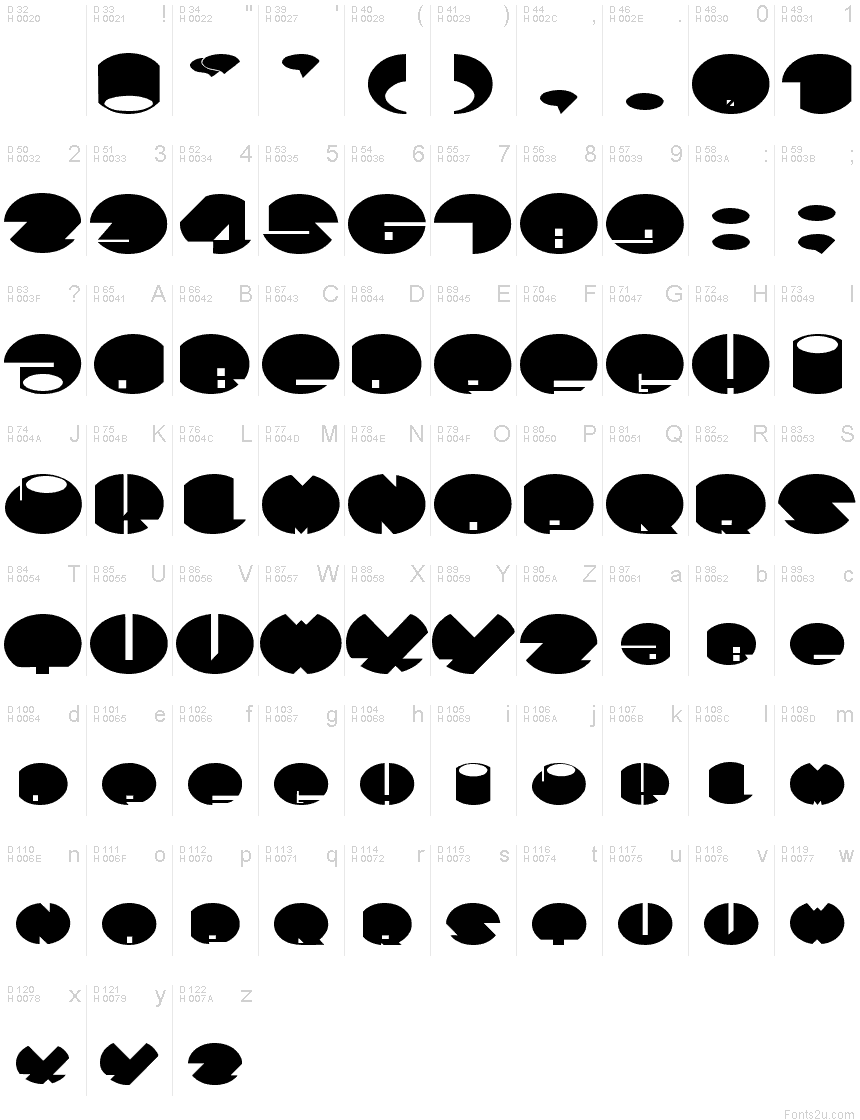
SpaceAce od Font"a"licious Fonts je bezplatné, výrazné písmo v retro-vesmírném duchu. Písmena jsou tvořena těžkými zaoblenými hmotami, které přerušují ostré horizontální řezy a klínovité zářezy. Celému písmu to dodává futuristický nádech „nízké oběžné dráhy“ 60. let, namísto jemného hippie stylu.
Hodí se na plakáty, obaly desek, arkádové letáky, titulky a výrazné obaly, kde toto bezplatné písmo dokáže samo o sobě vytvořit grafickou náladu. Protože jsou tvary tak kompaktní a skulpturální, dobře funguje i pro krátká loga, titulky na obálkách a velké iniciály, kde tato masivní kosmická silueta říká vše podstatné.